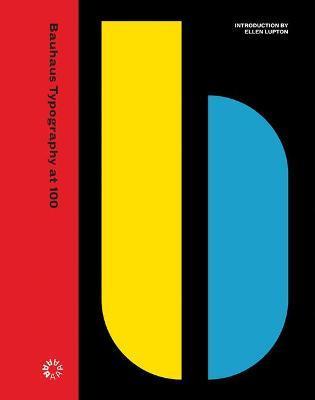
BAUHAUS TYPOGRAPHY AT 100
Livre neuf. Bauhaus Typography at 100. Catalogue de l'exposition présentée au Letterform Archiv de San Francisco de novembre 2021 à avril 2022. Ce livre rassemble plus de 150 publications et éphémérides liés à la question de la typographie et du graphisme au Bauhaus. Fondé en 1919 par l'architecte allemand Walter Gropius, le Bauhaus définit une culture visuelle très singulière et novatrice, imposant le sans serif dans la typographie et proposant des maquettes épurées et minimalistes. Ouvrage très illusté qui va chercher des exemples dans de nombreux domaines, sur des supports très différents (publications, revues, essais, expériences, New Typography...).